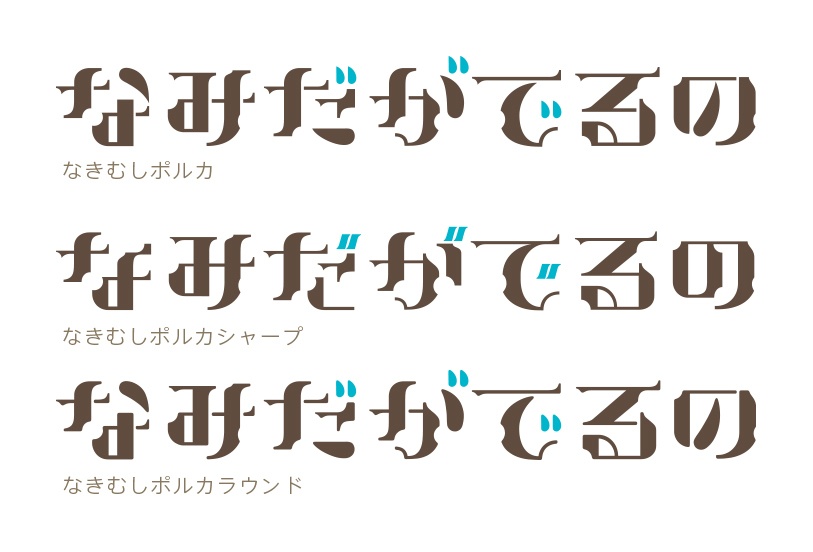
なきむしポルカ フォント
ゴシック主義的なデザインでありつつもキュートな雰囲気のフォントです。エキゾチック・レトロ・かわいい・ゴスロリなどインパクトのある用途にピッタリです。ロゴタイトルやキャッチフレーズなどの大きなサイズでの使い方に適しています。
収録文字数について
ひらがな、カタカナのみの書体になります。